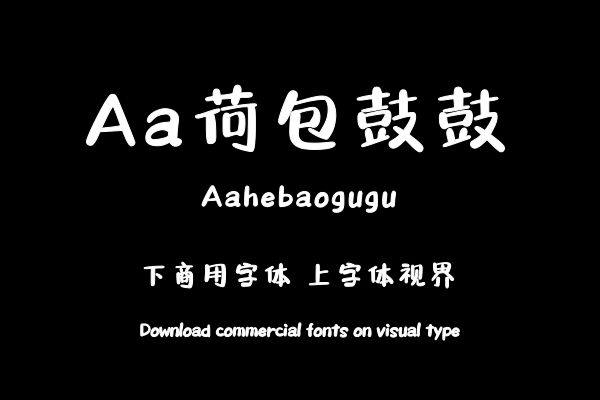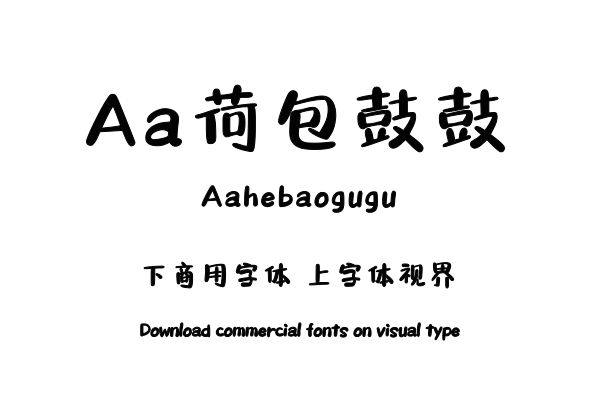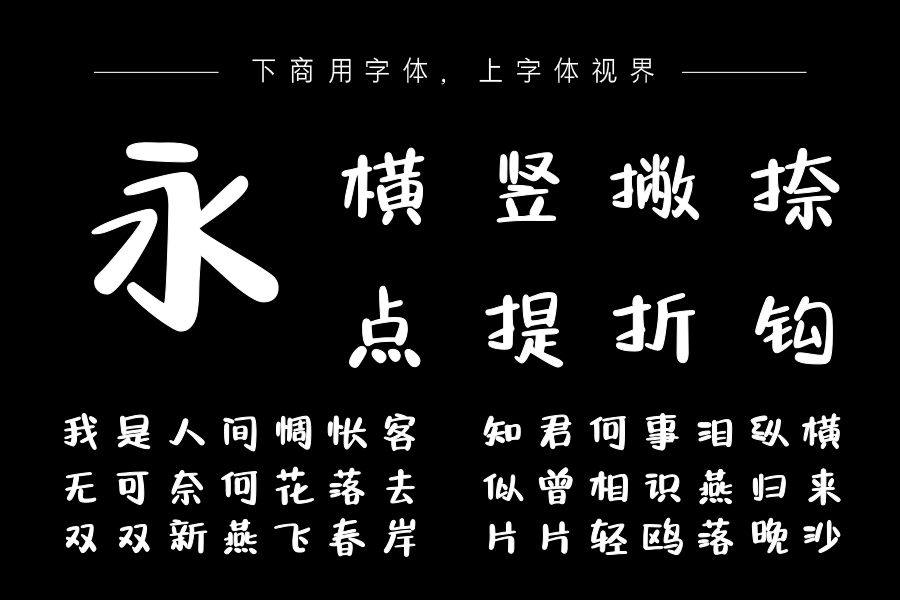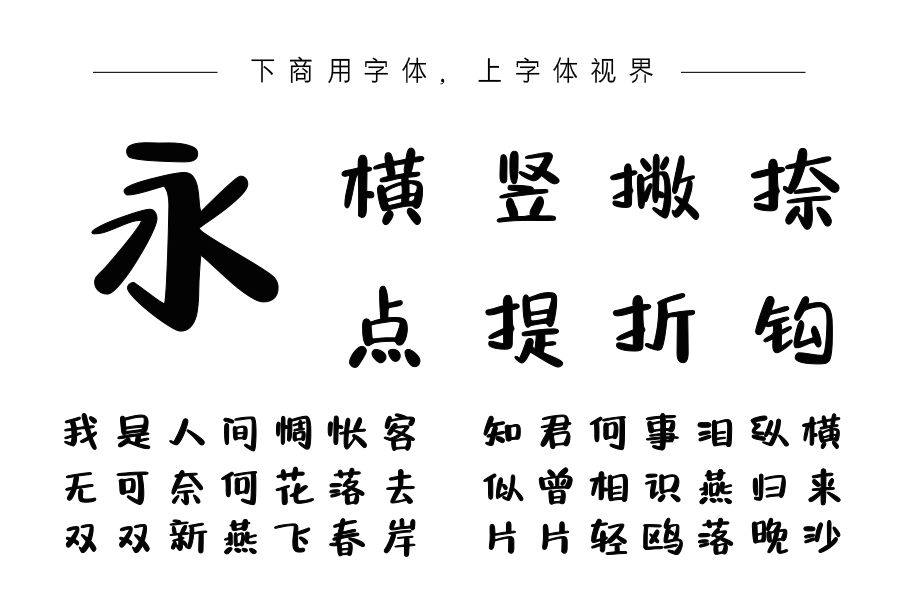
Aa荷包鼓鼓,作者是一名知名漫画家,是一款手绘风格的手写体。字形方中显长,笔画粗细对比明显、圆润有弹性。结构书写灵活,部件大小错落、有节奏。字体风格个性独特。多......购买须知:“下载服务费”与“字体VIP”所获得字体 仅用于个人非商用, 商用请联系付费授权。本字体为电脑用字,手机没有root权限不支持直接手机换字(手机如何root,请自行百度搜索教程)。购买前请先 了解清楚后再付款 ,字体为虚拟产品无法回收 一旦购买不支持退款。